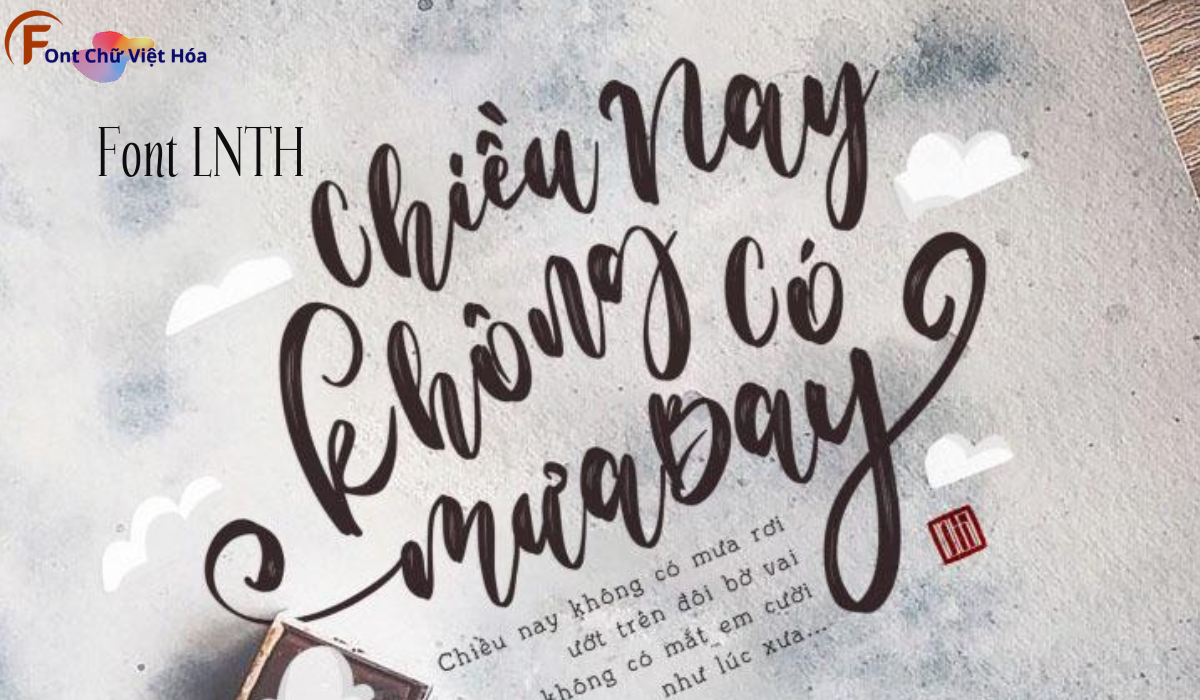
Font LNTH DeBorstel Brush Việt Hóa
Font LNTH DeBorstel Brush Việt Hóa là một font chữ nghệ thuật, thuộc bộ LNTH, với thiết kế như nét cọ vẽ tay. Phong cách của font này phù hợp với các dự án thiết kế cần sự sáng tạo và cá tính, như poster, bìa sách, hoặc thiệp mời. Font LNTH DeBorstel Brush Việt Hóa mang đến sự độc đáo và dễ nhận diện, ứng dụng trong các lĩnh vực sáng tạo. Đặc điểm hình dạng của font bao gồm các nét cọ tự nhiên và phóng khoáng, giúp tăng tính thẩm mỹ và sự chú ý. Việc Việt hóa font giúp người dùng dễ dàng sử dụng trong các thiết kế tiếng Việt, mang lại sự tiện lợi và linh hoạt.